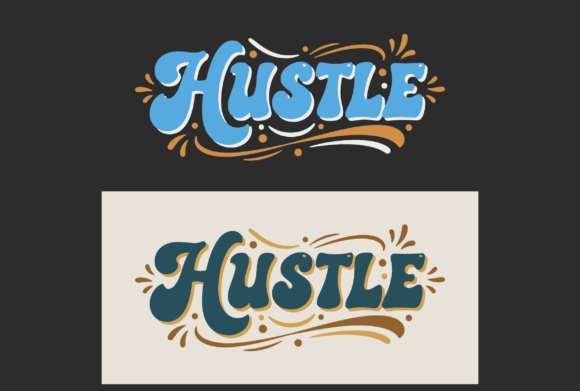
Hustle Retro Script Design
์˜ฌ๋ฐ”๋ฅธ ๋””์ž์ธ ์š”์†Œ๋ฅผ ์ฐพ๋Š” ๊ฒƒ์€ ์–ด๋ ค์šธ ์ˆ˜ ์žˆ์ง€๋งŒ Hustle Retro Script Design๋Š” ์ž‘์—…์„ ์ฆ‰์‹œ ํ–ฅ์ƒ์‹œํ‚ค๋Š” ๋›ฐ์–ด๋‚œ ์ปฌ๋ ‰์…˜์„ ์ œ๊ณตํ•ฉ๋‹ˆ๋‹ค.
POD(์ฃผ๋ฌธํ˜• ์ธ์‡„) ์ œํ’ˆ, ๊ฒฐํ˜ผ์‹ ์ดˆ๋Œ€์žฅ ๋˜๋Š” ์†Œ์…œ ๋ฏธ๋””์–ด ๊ทธ๋ž˜ํ”ฝ์„ ๋งŒ๋“ค ๋•Œ Hustle Retro Script Design๋Š” ์ด์ƒ์ ์ธ ์„ ํƒ์ž…๋‹ˆ๋‹ค.